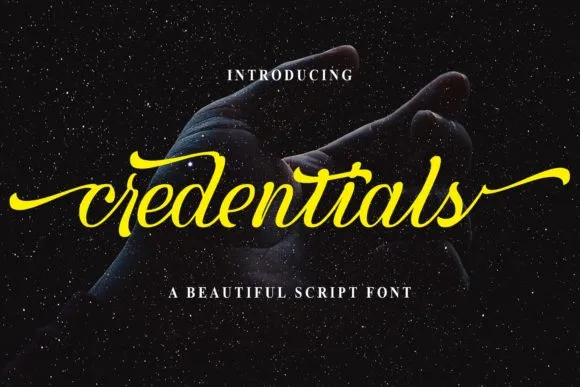
Credentials Script Font – Download Grátis
A “Credentials Script Font” é uma bela tipografia script que combina a elegância e a sofisticação do estilo antigo com a contemporaneidade do design moderno. Esta fonte de calligrafia personalizada contém inúmeros alternativos, criando um resultado limpo, forte e sofisticado. É perfeitamente adequada para diversos projetos, tanto para estilos urbanos quanto vintage. Suave e vibrante ao mesmo tempo, a “Credentials Script Font” é uma fonte de script de caráter dinâmico que se destaca por sua criatividade e originalidade. Ideal para aplicações como headline, posts e histórias no Instagram, logos, revistas e livros, cartões de cumprimentos e casamentos, embalagens, moda, maquiagem, estaçãoaria, etiquetas ou qualquer tipo de propósito publicitário. A fonte é uma ótima escolha para criar design que seja tanto atemporal quanto moderno, fazendo-o um recurso indispensável no seu portfólio de design gráfico.